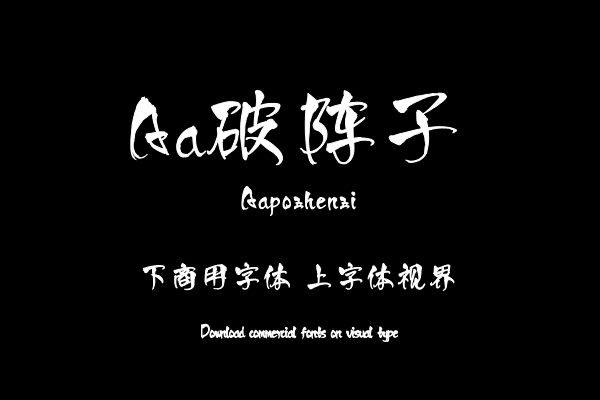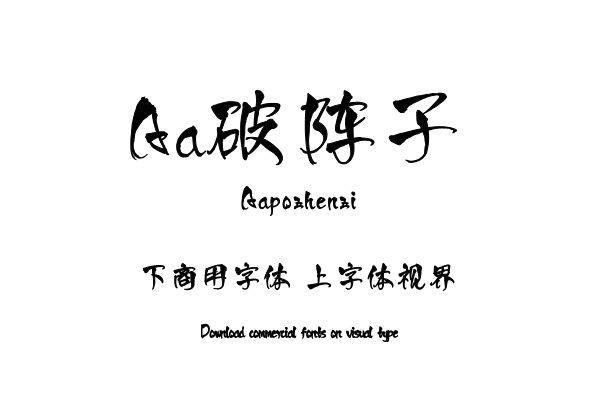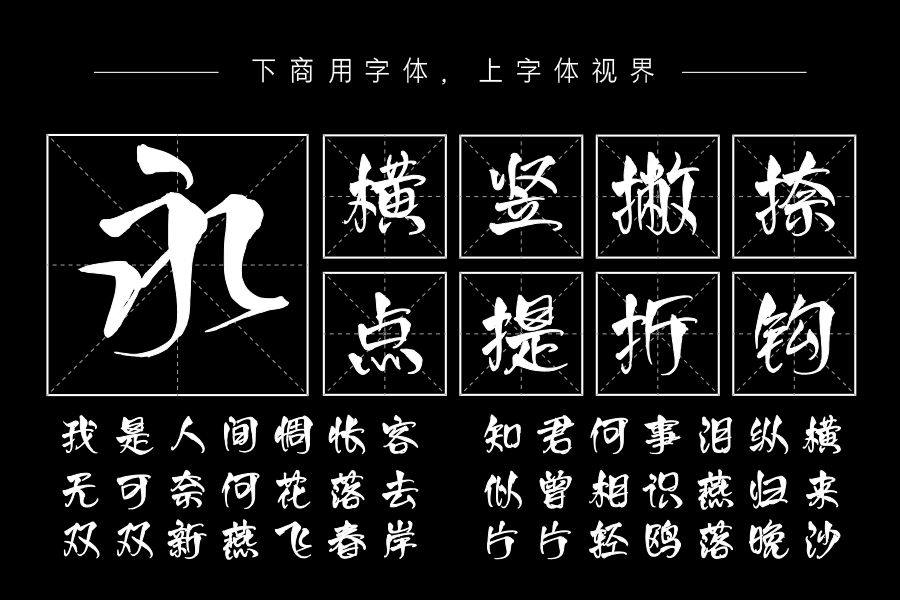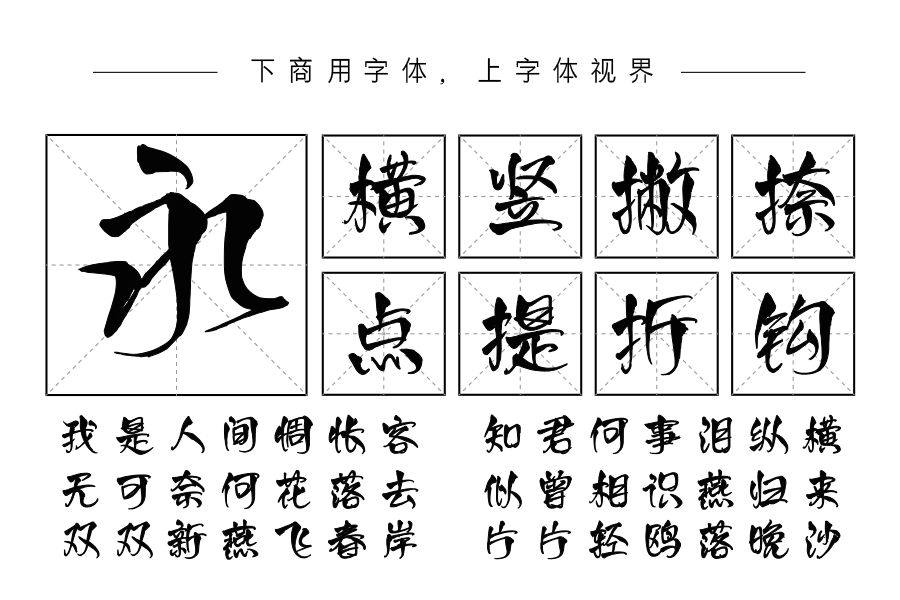
结合书法艺术与现代字体技术设计一款创意标题字体,突出潇洒气质,迎合当代商业环境对书法字体的需求变化。本款字体力求笔画流畅、字形饱满,用笔连续多变,风格癫狂洒脱。购买须知:“下载服务费”与“字体VIP”所获得字体 仅用于个人非商用, 商用请联系付费授权。本字体为电脑用字,手机没有root权限不支持直接手机换字(手机如何root,请自行百度搜索教程)。购买前请先 了解清楚后再付款 ,字体为虚拟产品无法回收 一旦购买不支持退款。